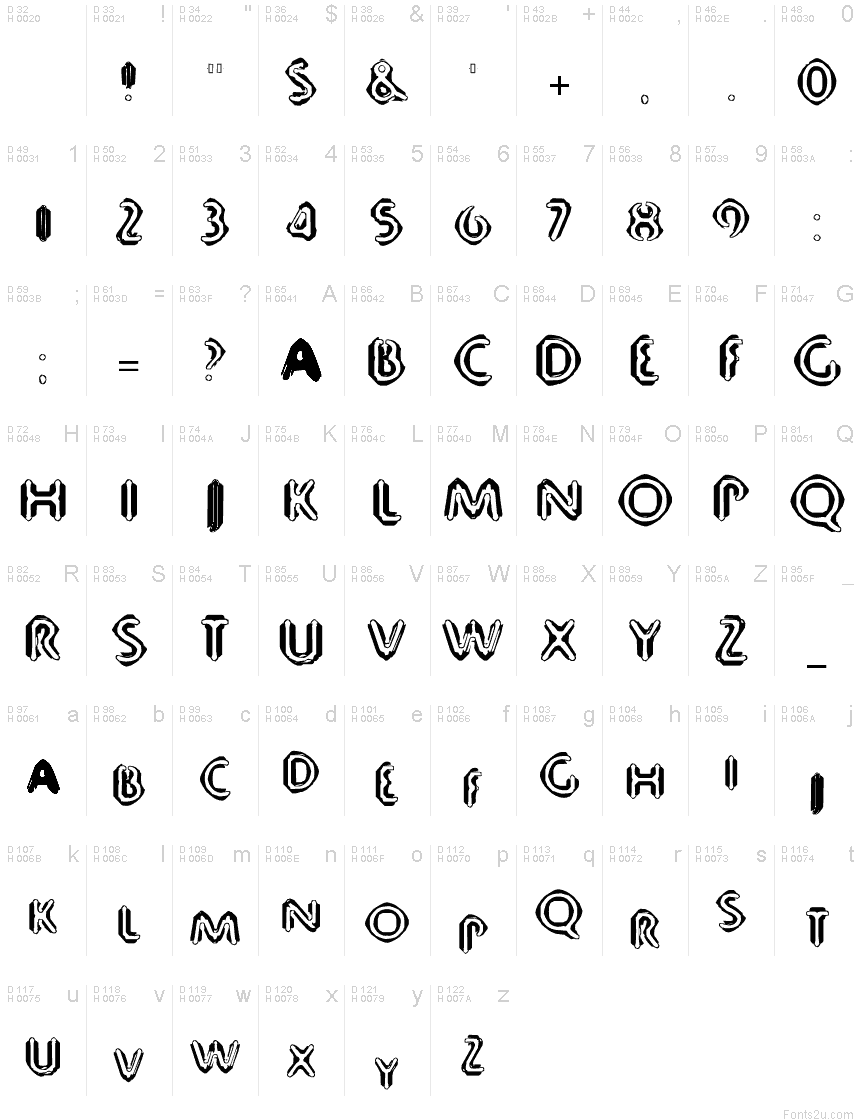
„80 Decibels“ je výrazné titulkové písmo, ze kterého vyzařuje šmrnc ošlehaný časem. Nerovnoměrné, erodované tvary písmen evokují průmyslovou estetiku a dodávají jakémukoli návrhu nádech drsné autentičnosti. Odvážné, rázné tahy a hranaté tvary vyjadřují surovou sílu, díky čemuž je toto písmo ideální volbou pro nadpisy, branding a prvky, které mají upoutat pozornost.
Jeho osobitý styl se skvěle hodí pro různorodé využití, od městského brandingu až po drsnější redakční sazbu, kde efektivně přitahuje pozornost a zanechává trvalý dojem.